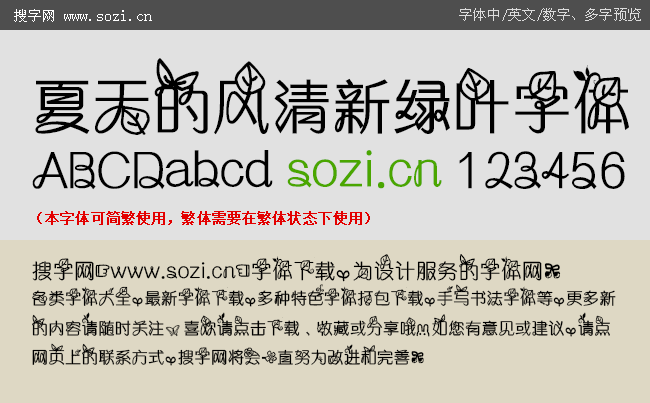
夏天的風(fēng)清新綠葉字體
搜字網(wǎng)提供一款夏天的風(fēng)清新綠葉字體中文手機(jī)字體下載,夏天的風(fēng)清新綠葉字體是由蒙納纖蘭體為原形,字體筆畫間加入了卡通綠葉圖案,蒙納纖蘭體端正大方,藝術(shù)美觀,加入點(diǎn)綴后增添了趣味性,適合喜歡個(gè)性的朋友下載安裝使用。